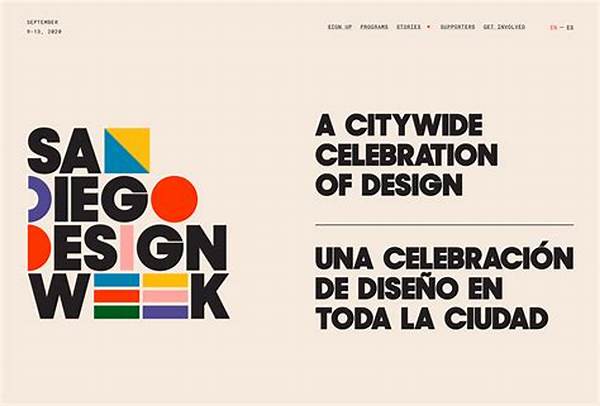
Hai! Pernah nggak kamu kepikiran, seperti apa sih font yang bisa bikin sebuah teks terasa berbeda dan unik? Kalau iya, kamu datang ke tempat yang tepat. Dalam dunia desain grafis, ada satu hal yang menarik perhatian banyak orang: eksplorasi desain font eksperimental. Yup, ini bukan sekadar mengganti jenis huruf dari Arial ke Times New Roman. Ini adalah dunia di mana imajinasi dan kreativitas jadi raja. Yuk, kita mulai petualangan kita ke dunia font yang keren ini!
Mengapa Eksplorasi Desain Font Eksperimental Penting?
Eksplorasi desain font eksperimental nggak cuma soal estetika, lho. Ketika kamu menggunakan font yang berbeda, kamu juga mengomunikasikan pesan yang berbeda. Font bisa jadi ekspresi perasaan, gagasan, atau bahkan budaya. Misalnya, ketika kamu melihat desain dengan font yang berkesan edgy dan futuristik, perasaan yang muncul bakal beda dibanding ketika kamu lihat font yang klasik dan elegan. Itulah kenapa eksplorasi desain font eksperimental bisa memberikan dampak signifikan pada hasil akhir sebuah desain. Selain itu, ini juga membuka peluang bagi desainer untuk mengekspresikan identitas mereka sendiri. Jadi, setiap karya jadi punya ciri khas dan nilai seni tersendiri yang unik, beda dari yang lain.
Melalui eksplorasi ini juga, desainer bisa menemukan solusi baru untuk tantangan yang kompleks. Misalnya, bagaimana cara membuat sebuah poster lebih menarik di tengah keramaian? Atau, bagaimana menghadirkan pengalaman visual yang segar ke publik? Jadi, ketika audiens melihat desain kita, mereka bakal merasakan pengalaman yang sama sekali baru. Memang, nggak semua eksperimen bakal sukses, tapi dari situ kita bisa belajar dan tumbuh. Siapa tahu, font eksperimental yang kita buat, malah jadi tren di masa depan kan?
Eksplorasi desain font eksperimental juga membantu dalam menggingatkan kita tentang apa yang dimungkinkan dalam dunia desain. Ini menginspirasi desainer lain untuk memikirkan cara berbeda dalam mengolah teks. Jadi, tidak hanya berhenti pada membuat sesuatu yang sekadar “cukup bagus,” tetapi juga merangsang diskusi tentang apa yang dianggap mungkin dalam bidang kreatif ini. Sehingga, eksplorasi ini tidak hanya memperkaya karya individu tetapi juga memperluas batas dunia desain font itu sendiri.
Langkah-Langkah dalam Eksplorasi Desain Font Eksperimental
1. Mengidentifikasi Tujuan dan Fungsi: Pertama-tama, tentukan tujuan font tersebut. Apakah untuk poster musik punk? Atau untuk branding kafe vintage? Eksplorasi desain font eksperimental harus dimulai dari sini.
2. Menggali Inspirasi: Selanjutnya, cari inspirasi sebanyak mungkin. Bisa dari sejarah tipografi, atau dari seni modern. Kadang inspirasi bisa muncul dari hal-hal yang di luar dugaan.
3. Memahami Dasar Tipografi dan Desain: Eksplorasi desain font eksperimental tetap butuh pemahaman dasar. Sebelum membuat sesuatu yang baru, pahami dulu dasar-dasarnya.
4. Melakukan Eksperimen: Nah, kini saatnya untuk bereksperimen! Gabungkan berbagai elemen yang telah kamu pelajari dan coba sesuatu yang belum pernah ada sebelumnya.
5. Feedback dan Revisi: Jangan lupa untuk meminta masukan dari orang lain. Kadang masukan bisa membuka wawasan baru yang nggak kita sadari sebelumnya.
Tantangan yang Dihadapi dalam Eksplorasi Desain Font Eksperimental
Melakukan eksplorasi desain font eksperimental bukan tanpa tantangan. Salah satu rintangan terbesar adalah menemukan keseimbangan antara membuat sesuatu yang inovatif tanpa mengorbankan keterbacaan. Ini adalah tantangan bagi desainer untuk mendorong batas kreativitas sekaligus memastikan bahwa hasil akhir tetap berfungsi dengan baik. Keseimbangan ini penting karena pada akhirnya, font harus bisa meninggalkan kesan tanpa membuat pembaca bingung.
Selain itu, tantangan lain adalah sumber daya. Tidak setiap desainer memiliki akses ke perangkat lunak atau alat yang nodigunakan untuk bereksplorasi. Namun, keterbatasan ini seringkali mendorong kreativitas ke arah yang tidak terduga. Sebuah ide bisa lahir dari keterbatasan itu sendiri dan menghasilkan karya yang benar-benar inovatif. Eksplorasi desain font eksperimental adalah tentang bagaimana mengubah keterbatasan menjadi peluang.
Mengapa Bereksperimen dengan Font Itu Menyenangkan
1. Kreativitas Tanpa Batas: Eksplorasi desain font eksperimental memberi kebebasan bagi desainer untuk bermain dan berekspresi.
2. Menyegarkan Perspektif: Bereksperimen dengan font adalah cara lain untuk melihat desain dari sudut pandang yang berbeda.
3. Kesempatan Belajar: Setiap eksperimen adalah peluang untuk belajar sesuatu yang baru, baik itu kesalahan atau sukses besar.
4. Memicu Inspirasi: Kadang, dari satu eksperimen, inspirasi untuk proyek lain bisa muncul.
5. Penghargaan Seni: Font eksperimental sering kali lebih dihargai sebagai bentuk seni. Ini adalah kesempatan untuk menciptakan sesuatu yang memiliki nilai estetika tinggi dan bisa dinikmati orang lain bukan hanya sebagai teks, tetapi juga sebagai karya seni.
Pentingnya Platform Digital dalam Eksplorasi Desain Font Eksperimental
Dalam era digital ini, ekslporasi desain font eksperimental lebih mudah dilakukan. Internet menyediakan akses cepat ke berbagai sumber daya yang sangat dibutuhkan desainer. Banyak platform digital menawarkan alat dan fitur yang memudahkan desainer bereksperimen dan berbagi hasil karyanya. Tentu saja, ini juga membuka kemungkinan kolaborasi antara desainer dari berbagai belahan dunia.
Pada akhirnya, hasil dari eksplorasi ini bukan cuma sekadar font yang menarik. Lebih dari itu, ini adalah seni yang memiliki makna dan bisa merangsang perasaan. Ketika kita berhasil menghasilkan desain yang unik dan berbeda, itulah kepuasan tersendiri. Eksplorasi desain font eksperimental bisa mengubah cara kita memandang desain, dan tentunya, ini adalah perjalanan yang layak untuk diambil. Mari kita terus bereksperimen dan menciptakan sesuatu yang luar biasa!